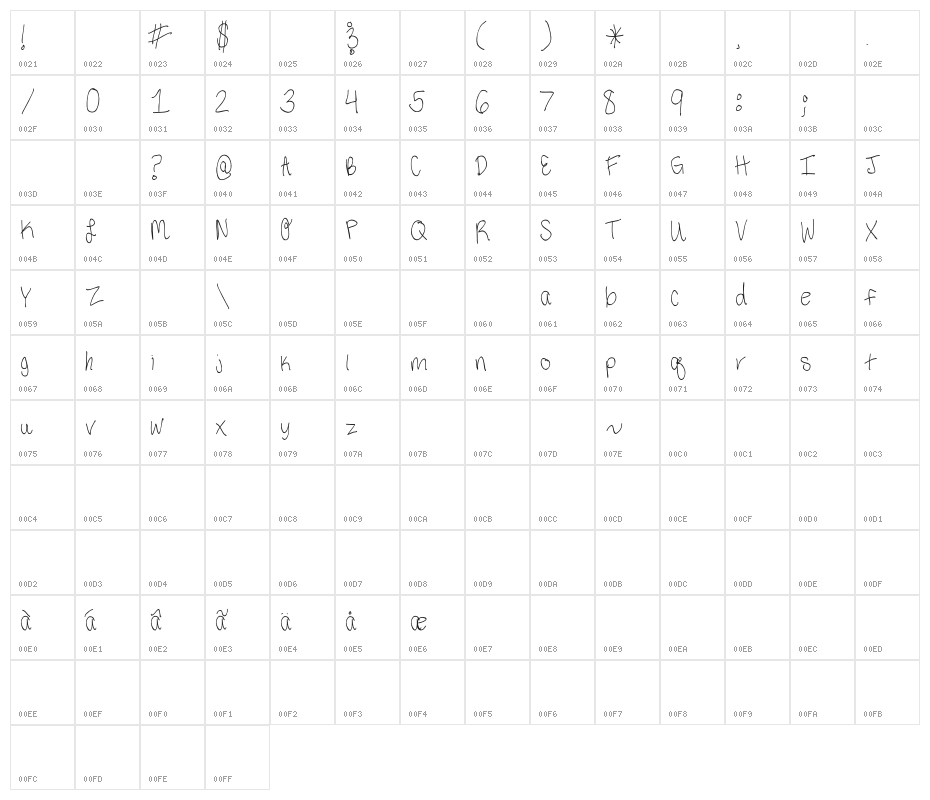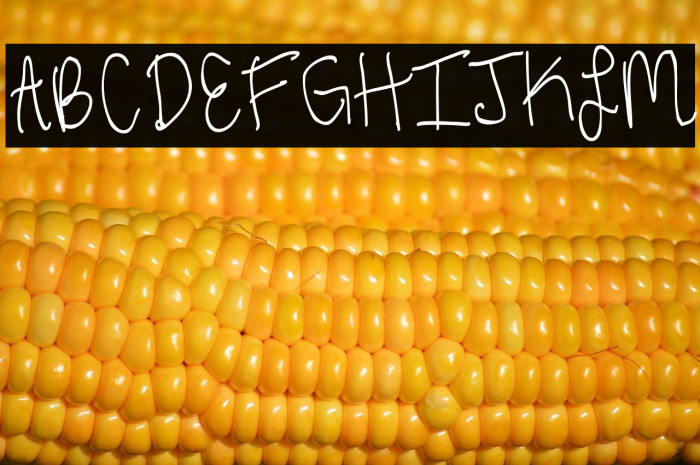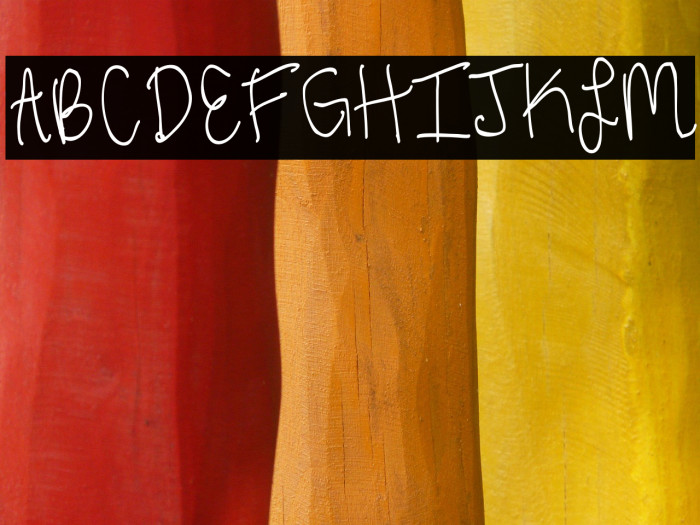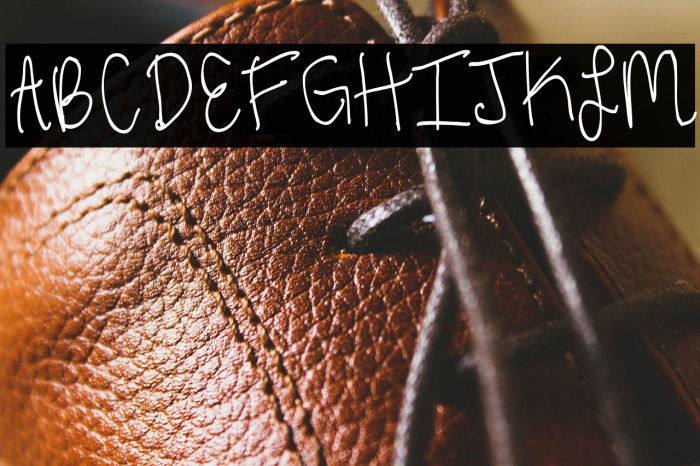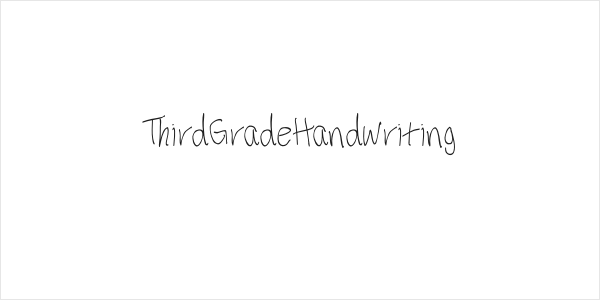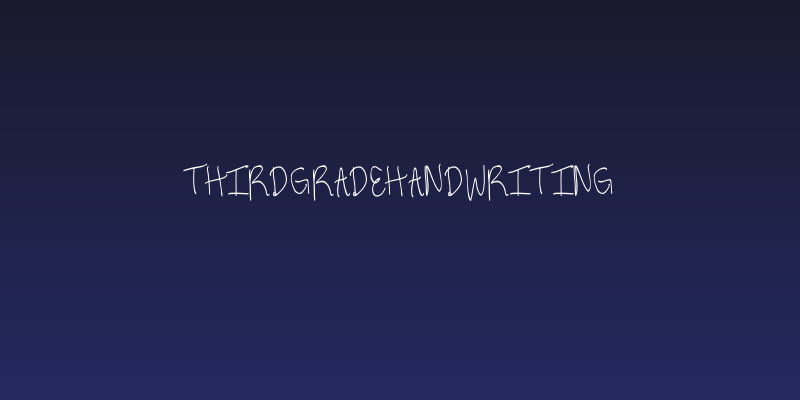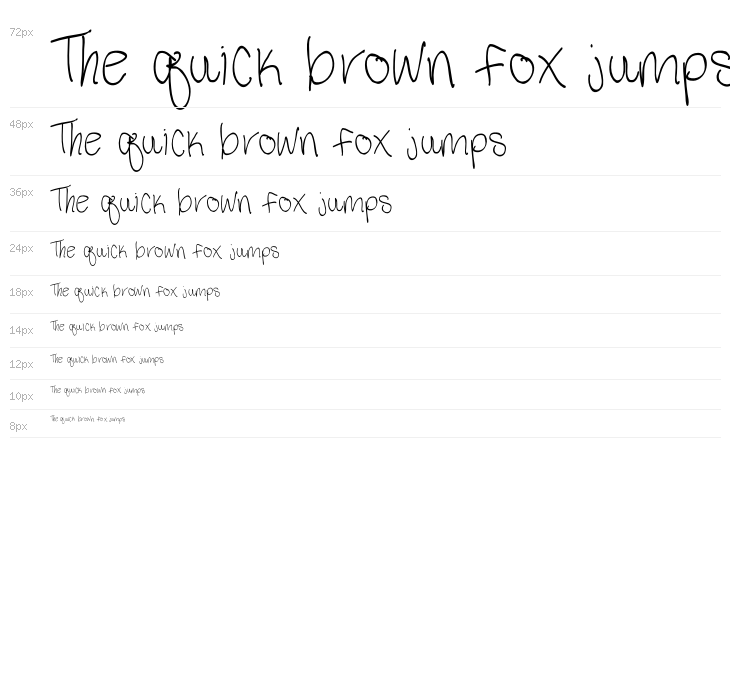
ThirdGradeHandwriting Font
| Style général | Playful, Informal, Childlike |
| Cas d'utilisation | Educational materials, Children’s books, Informal notes |
| Projets proposés | Children’s books, educational materials, greeting cards, informal invitations, playful branding. |